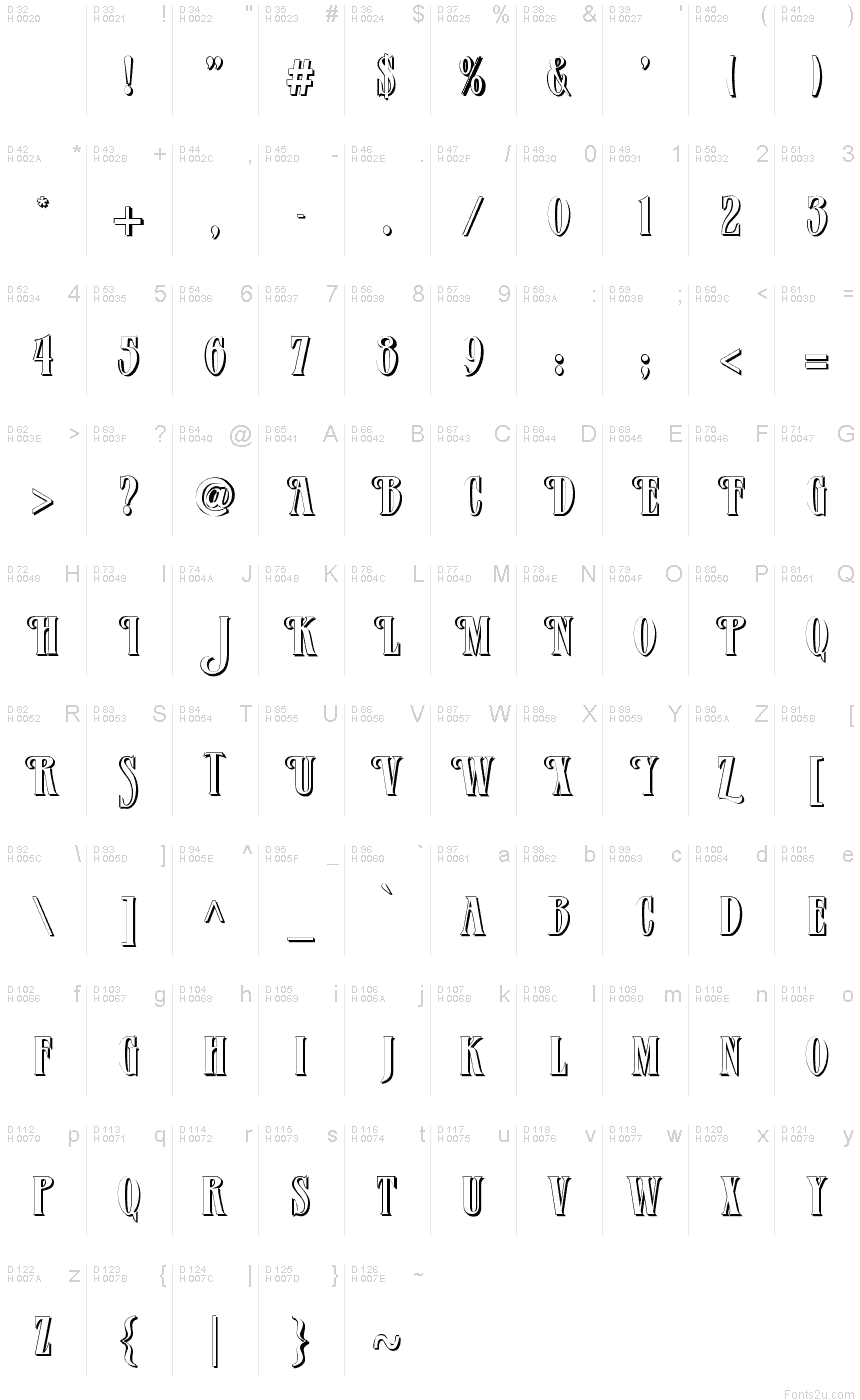
Verve Shadow, digitalisiert und gehintet von Dieter Steffmann, ist eine kostenlose Retro-Display-Schrift mit dem Flair alter Plakatmalerei. Die Großbuchstaben wirken hoch und theatralisch, mit scharfen Serifen, geschwungenen Öffnungen und einem integrierten Schatten, der den Buchstaben eine plastische, geschnitzte Wirkung verleiht, ohne ihren präzisen Vintage-Rhythmus zu verlieren.
Damit ist diese kostenlose Schrift die ideale Wahl für Plakatüberschriften, Verpackungsetiketten, Magazin-Cover, Branding für Bars und Cafés sowie Titelkarten, die einen historischen Look statt einer neutralen Headline benötigen. Sie eignet sich zudem hervorragend für Monogramme und kurze Wortmarken, da der Schatten fester Bestandteil des Designs ist und selbst kurzen Wörtern eine bühnenreife, nostalgische Ausstrahlung verleiht.